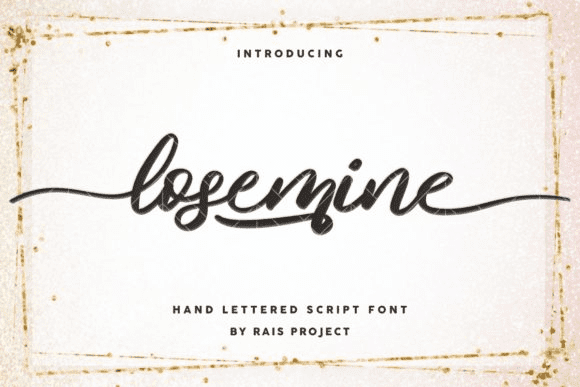
Название: Losemine Font
Лоземин - это тонкий и элегантный рукописный шрифт.
Его четкие и хорошо закруглённые буквы делают этот шрифт шедевром.
Влюбитесь в его невероятно универсальный стиль и используйте его для создания эффектных дизайнов!
Название: Losemine Font
Лоземин - это тонкий и элегантный рукописный шрифт.
Его четкие и хорошо закруглённые буквы делают этот шрифт шедевром.
Влюбитесь в его невероятно универсальный стиль и используйте его для создания эффектных дизайнов!